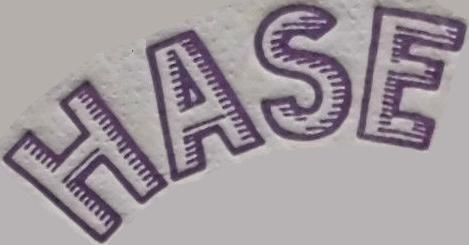
Vermutete Bierdeckel-Schriftart, etwa um 1930
bezüglich der gesuchten Schrift habe ich bereits Einiges gelesen und vermute mittlerweile, dass es sie handmade ist - oder wisst Ihr mehr?
Leider habe ich nur noch etwa ein Viertel eines Bierdeckels (?), auf dem die Buchstaben "H", "A", "S" und "E" zu sehen sind (siehe Bild). Eventuell reicht dies bereits für Hinweise.
Falls die exakte Schrift tatsächlich nicht existieren sollte, wäre ich natürlich auch für ähnliche Schriften sehr dankbar, da sie mir sehr gut gefällt.
Ich würde in ndiesem Fall nicht nur von neiner Vermutung ausgehen, sondern von einer Gewissheit, dass die handgemacht ist.
Grund: es gab damals praktisch keine Möglichkeit, Satzschriften so zu verformen, dass sie sich einer Kreisform anpassen. Auch ist das deutlich an den doch etwas eierigen Formen (besonders beim S) und den ungleichen Abständen der Schraffur zu erkennen. Im übrigen gab es - bis etwa in die 1970er Jahre viele Lehrbücher, in denen anhand typischer, einfacher Schriftformen der derart handwerkliche Schriftentwurf gelehrt wurde. Schildermaler, Steinmetze, Werbe-Grafiker, aber auch "einfache" KFZ-Lackiereer mussten das einfach lernen, um Beschriftungen überhaupt anbringen zu künnen, was zu einem reichen Schatz unterschiedlichster Schriften führte. Praktisch jedes Schild, sofern es nicht in Emaile schabloniert oder siebgedruckt später auf Acryl-Schildern war, war dann oft eigenständig. Manche Schriftstile, die dann von den Schildermaler-Kollegen immer wieder aufgegriffen wurde, prägten dann oft das sonst eigenständige Bild unterschiedlicher Städte.
(davon abgesehen sind letztlich auch alle alten Satzschriften, bei aller typografischer Präzision, auch handgemacht)
Und in diesem Fall wird wahrscheinlich dieses doch etwas rauhbeing ungelenke gerade den Charme dieser Schrift ausmachen, der möglicherweise verloren gehen kann, baut man sie mit der Präzision, die der Computer heute ermöglicht als kompletten, und dann für den Satz in gerader Linie nachbaut.
Gewiss hat die Computertechnik einiges an Erleichterungen gebracht, und praktisch jeder ist heute in der Lage, äußerst saubere Beschriftungen anzufertigen (auch wenn manche auch hiermit grausames zu Stande bringen), aber das Stadtbild in vielen Regionen hat sich damit auch vereinheitlicht, man sieht praktisch überall die Schriften, die mit dem großen Grafik-Programmen mit ausgeliefert wurden, und so manche Schrift ist dann allgegenwärtig.
Ich mache mir eigentlich keine so große Hoffnung, dass du eine nahezu identische Schrift findest. Trotzdem sollte es möglich sein, eine solche zu erzeugen - und die ist dann (auch mit Computer-Hilfe) - letztlich auch wieder handgemacht...
Danke für die ausführliche Antwort. Werde versuchen, mithilfe von Photoshop eine serifenlose Schrift zu setzen, der ich zunächst mal manuell diese reliefartigen "Schattenstriche" mitgebe. Mal sehen, was dabei herauskommt.